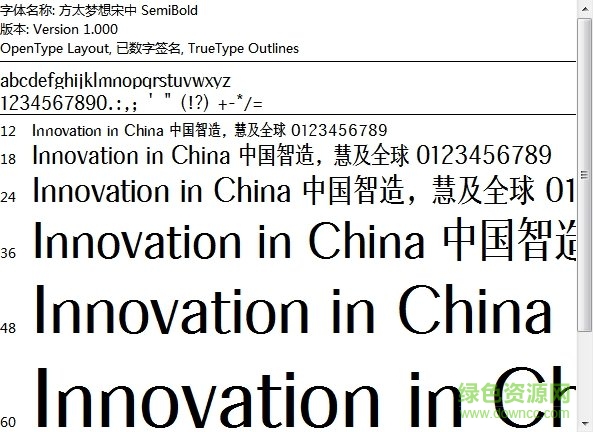
方太夢想宋是方太集團(tuán)推出的一款專屬宋體,有三個(gè)字重:方太夢想宋粗、方太夢想宋中、方太夢想宋細(xì),具有印刷雕刻字體的特色,造型精簡結(jié)構(gòu)勻稱,集現(xiàn)代時(shí)尚感和古風(fēng)藝術(shù)感為一體,十分出眾,快來綠色資源網(wǎng)下載吧!
“方太夢想宋”后面有著一個(gè)關(guān)乎夢想的故事:一位普通媽媽設(shè)計(jì)師,在方太組建的設(shè)計(jì)團(tuán)隊(duì)的幫助下,經(jīng)過14個(gè)月打造出的「方太夢想宋」,實(shí)現(xiàn)了自己設(shè)計(jì)字體的夢想。這位媽媽30年的等待與醞釀,化為了具體的6763個(gè)漢字。
方太夢想宋基于雕版體開發(fā),創(chuàng)作時(shí)從大量雕版資料從中尋找字體原型,以“形、意、度”為標(biāo)準(zhǔn)著手,形即結(jié)構(gòu),意即神態(tài),度即平衡,讓方太夢想宋逐步成型。
新字體取名“方太夢想宋”,按GB2312標(biāo)準(zhǔn)設(shè)計(jì),共7000字。這系列字體共有三個(gè)字重,字形修長,筆畫方折,重心略向右上翹,秀麗而不失風(fēng)骨。
考慮到字體的應(yīng)用屬性,方太夢想宋在保留雕版字體美感的同時(shí),還要適應(yīng)現(xiàn)代媒介的傳播特性,因此筆畫要更加精煉。字體細(xì)節(jié)處理結(jié)合了現(xiàn)代字體平滑、利落的輪廓特性,古樸而兼有現(xiàn)代構(gòu)成的美感,實(shí)現(xiàn)了閱讀的流暢性。
從結(jié)構(gòu)上,方太夢想宋比較接近于美黑體,筆畫比美黑更具鋒芒,整體閱讀性不及美黑體。